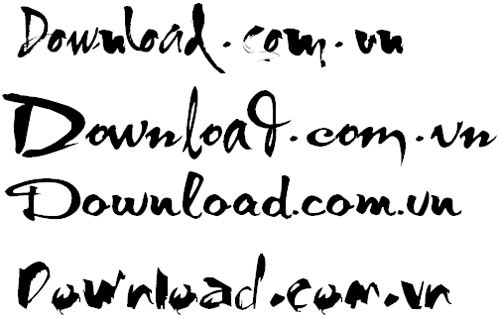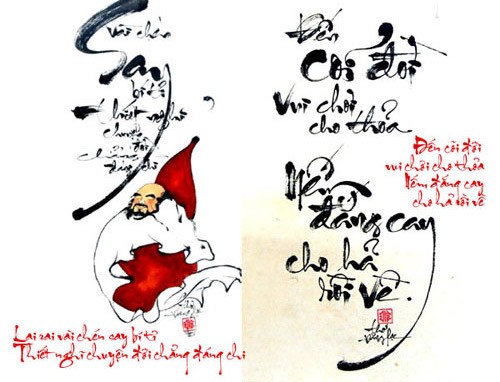
Bộ Font Thư Pháp: Công Cụ Nghệ Thuật Viết Chữ Việt
Bộ Font thư pháp là một bộ sưu tập font chữ tiếng Việt được thiết kế theo phong cách thư pháp nghệ thuật, hoàn toàn miễn phí. Bộ font này cho phép người dùng tự do sáng tạo những câu đối Tết đẹp mắt, mang phong cách chuyên nghiệp như một Ông Đồ thực thụ.
Với Bộ Font thư pháp, bạn có thể thỏa sức thể hiện cá tính qua những câu đối độc đáo, hoặc tạo ra các hình ảnh ấn tượng với sự kết hợp tinh tế giữa chữ và hình ảnh.
Tạo Hình Nền Tết 2021 Độc Đáo
Khi Tết Nguyên Đán đang đến gần, việc tải hình ảnh nền Tết 2021 cho máy tính là một lựa chọn phổ biến. Tuy nhiên, bạn hoàn toàn có thể tự tạo ra những hình nền Tết 2021 mang đậm dấu ấn cá nhân bằng cách sử dụng bộ chữ thư pháp này.
Điều này giúp bạn sở hữu một không gian máy tính độc đáo và thể hiện phong cách riêng trong dịp lễ quan trọng.
Sự Đa Dạng và Tinh Tế Trong Thiết Kế
Bộ font thư pháp cung cấp nhiều mẫu chữ khác nhau, đáp ứng mọi sở thích và phong cách cá nhân. Mỗi mẫu chữ đều được thiết kế tỉ mỉ, thể hiện sự tinh tế trong từng nét bút.
Sự cân bằng giữa nét thanh và nét đậm trong mỗi font chữ được điều chỉnh kỹ lưỡng, nhằm đạt được giá trị nghệ thuật cao nhất trong nghệ thuật viết chữ đẹp.
Đặc điểm nổi bật của Bộ Font Thư pháp
Tính thẩm mỹ cao là một trong những yếu tố quan trọng nhất của font chữ thư pháp. Những đường nét mềm mại, uyển chuyển được tạo ra mang đến vẻ đẹp độc đáo và sức hút khó cưỡng. Sự nhấn nhá tinh tế giữa nét thanh và nét đậm góp phần thu hút ánh nhìn và làm nổi bật các ấn phẩm thiết kế.
So với các loại font thông thường, font chữ thư pháp sở hữu khả năng truyền tải thông điệp một cách hiệu quả hơn. Mỗi nét chữ không chỉ đơn thuần là ký tự, mà còn là sự thể hiện cảm xúc và ý đồ sáng tạo của người thiết kế.
Tính độc đáo và khác biệt là dấu ấn riêng của mỗi font chữ thư pháp. Mỗi font mang một vẻ đẹp riêng, phản ánh phong cách và gu thẩm mỹ của người sáng tạo, giúp tăng cường tính cá nhân hóa và tạo dấu ấn đặc trưng.
Font chữ thư pháp thường khơi gợi những cảm xúc và vẻ hoài cổ. Nhờ những đường uốn lượn mềm mại, tựa như nét bút lông truyền thống, chúng mang đến cảm giác sang trọng, lãng mạn và dịu dàng.
Sự đa dạng về kiểu chữ là một lợi thế lớn của thư pháp. Người dùng có thể thoải mái lựa chọn font chữ phù hợp nhất với nội dung và mục đích sử dụng của văn bản.
Font chữ thư pháp mang đến sự giống với nét viết tay chân thực, như thể được viết bởi một nghệ nhân thư pháp tài ba với những nét chữ dứt khoát và mạnh mẽ.
Tính tương thích cao với bộ gõ tiếng Việt giúp người dùng dễ dàng sử dụng font chữ thư pháp trong các ứng dụng khác nhau.
Thư pháp – Nghệ thuật Viết Chữ Đẹp
Thư pháp được hiểu là một loại hình nghệ thuật tập trung vào việc viết chữ đẹp. Do đó, trước hết, cần nhận thức thư pháp như một bộ môn nghệ thuật, và sản phẩm của nó chính là những tác phẩm nghệ thuật độc đáo.
Bộ Font thư pháp này bao gồm nhiều kiểu chữ đa dạng, với các hoa văn và thiết kế khác nhau, rất phù hợp cho những ai yêu thích nghệ thuật chữ và muốn tạo ra những tấm thiệp chúc mừng ấn tượng.
Font thư pháp được định nghĩa như thế nào?
- Font thư pháp là một loại chữ được thiết kế để mô phỏng các đường nét viết tay truyền thống, thường mang đậm dấu ấn của phong cách Á Đông. Đặc trưng của chúng là sự uyển chuyển, mềm mại, và khả năng truyền tải những cảm xúc cổ điển, trang trọng hoặc lãng mạn. Các font này thường được ứng dụng trong các thiết kế liên quan đến Tết Nguyên Đán, nghệ thuật thư pháp Việt Nam, thiệp chúc mừng, tranh câu đối, và nhiều lĩnh vực khác.